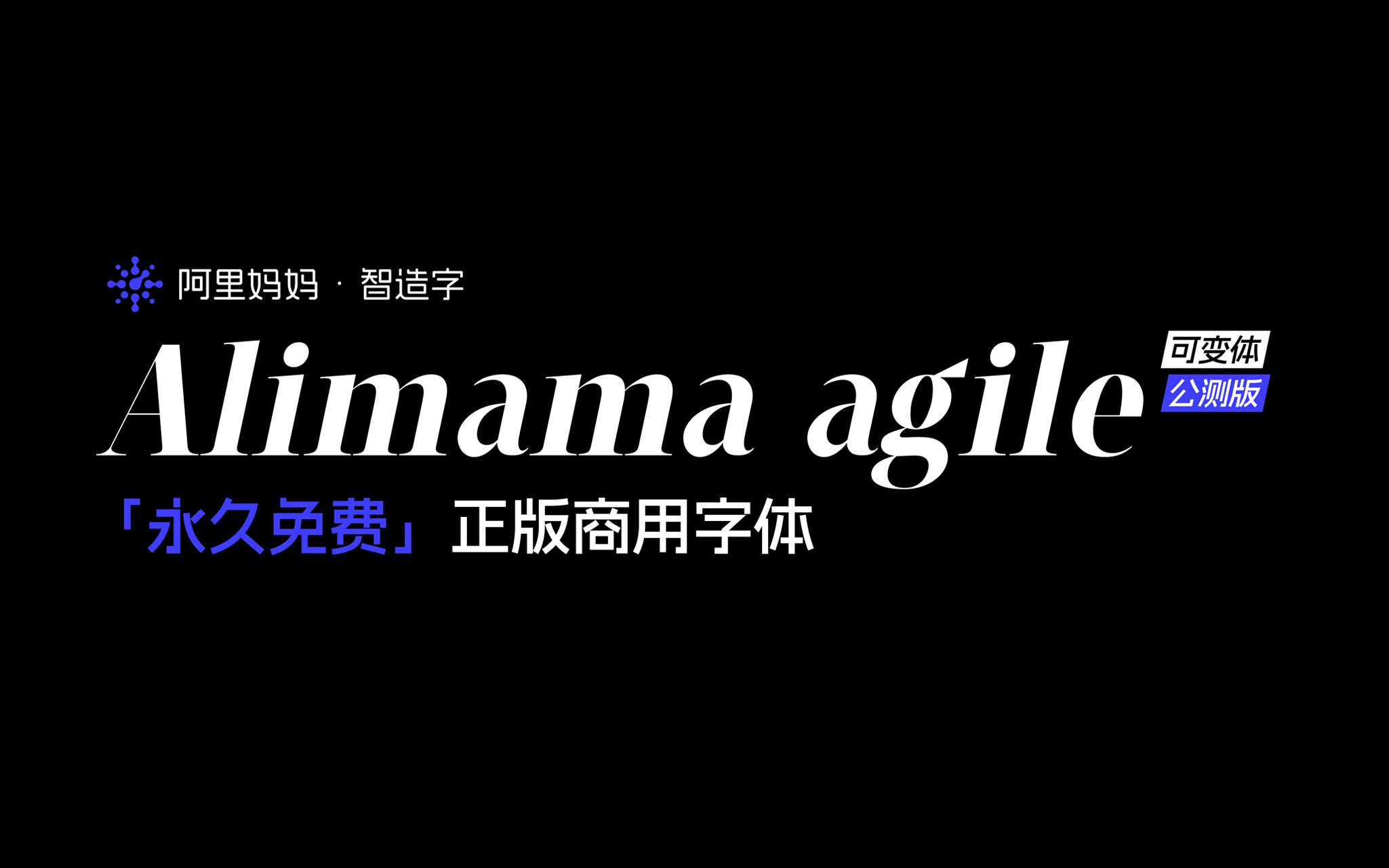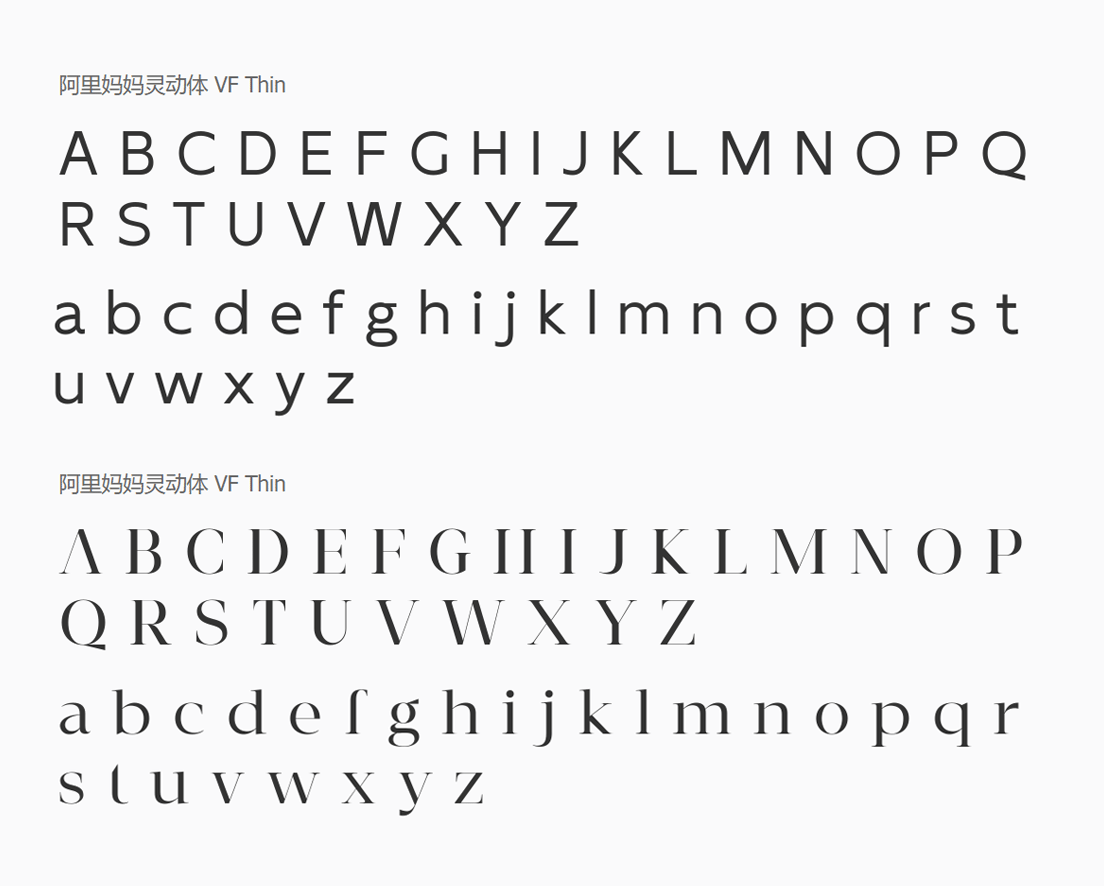
阿里妈妈灵动体(alimama agile)是一款西文可变字体,是阿里妈妈·智造字首次尝试研发的多轴可变的西文字体,包含了字重、字宽、倾斜、衬线四种可变轴,英文大小写共52个;常用标点符号共68个,总计120个字符。
阿里妈妈灵动体(alimama agile)字形预览 | 免费商用可变英文(西文)字体下载